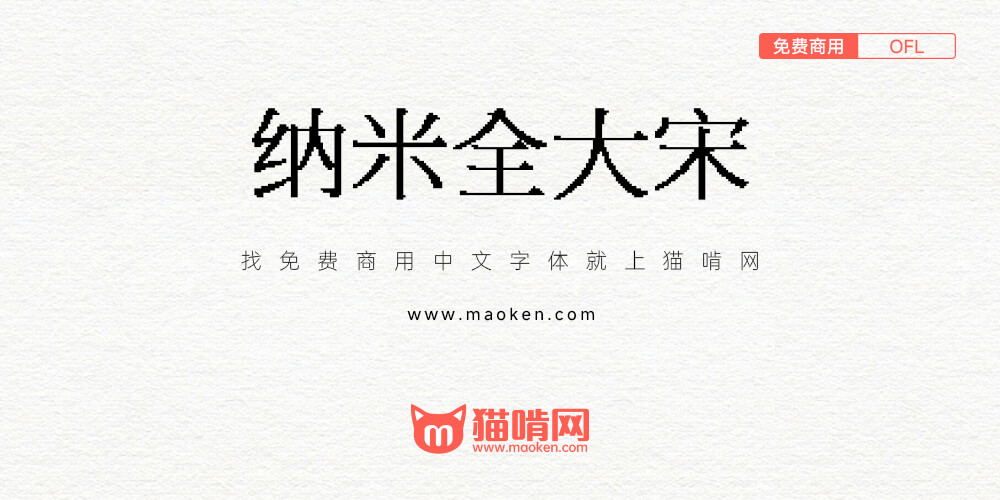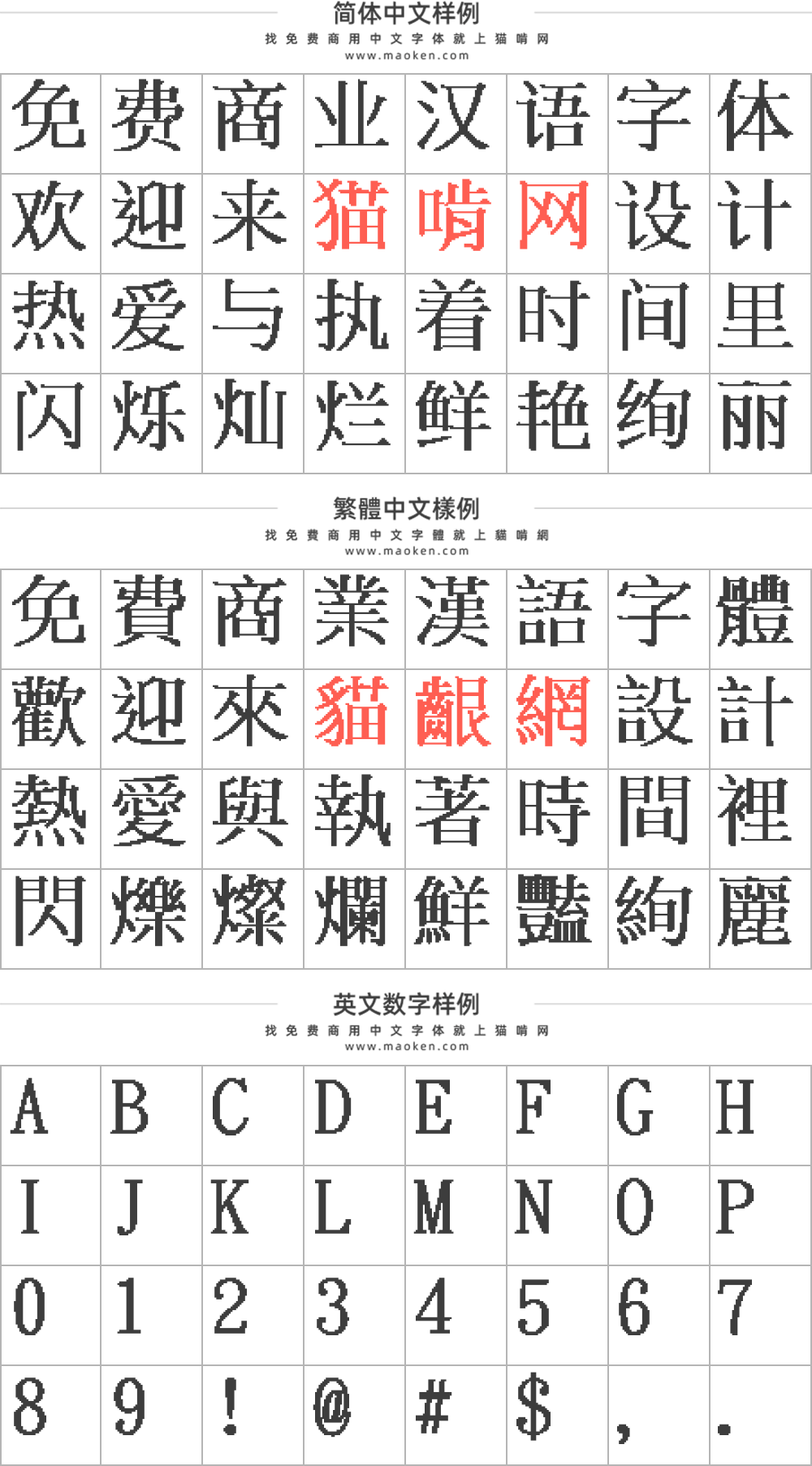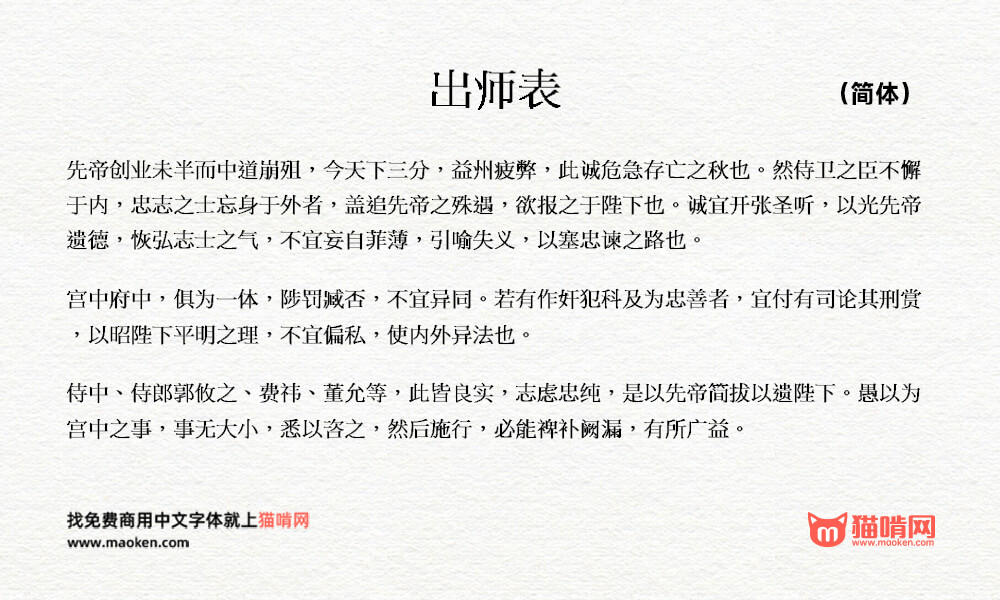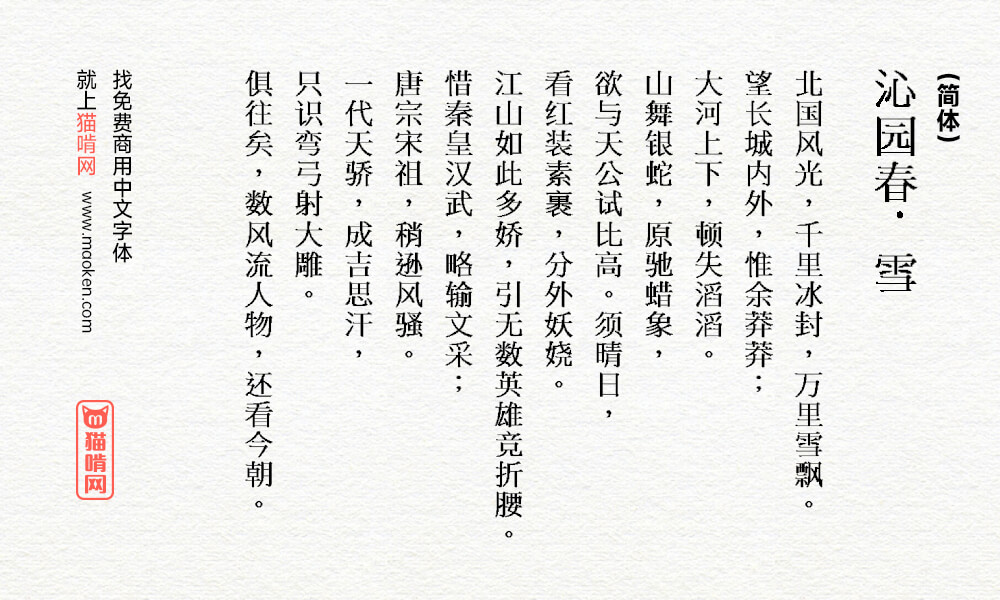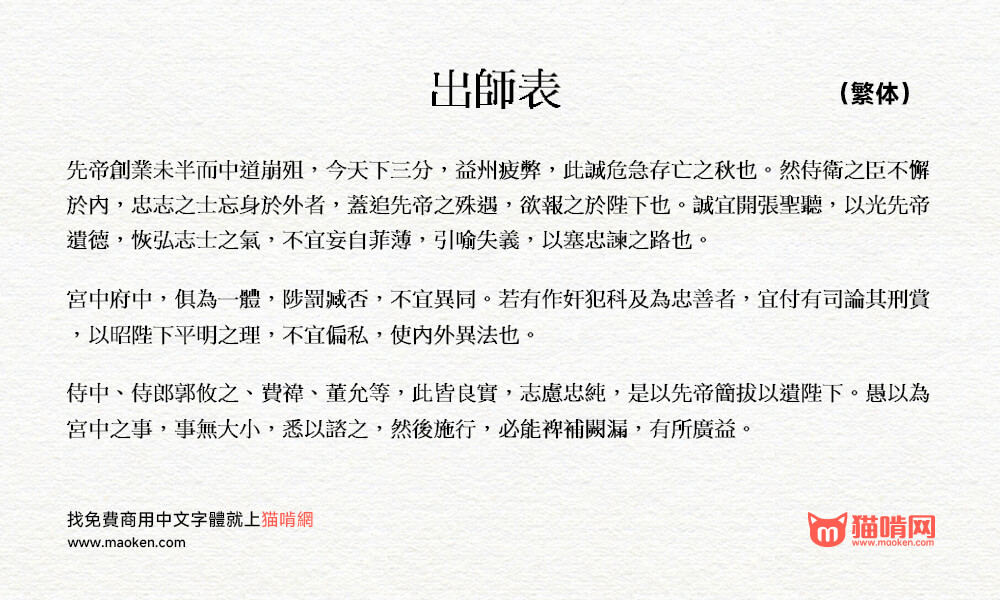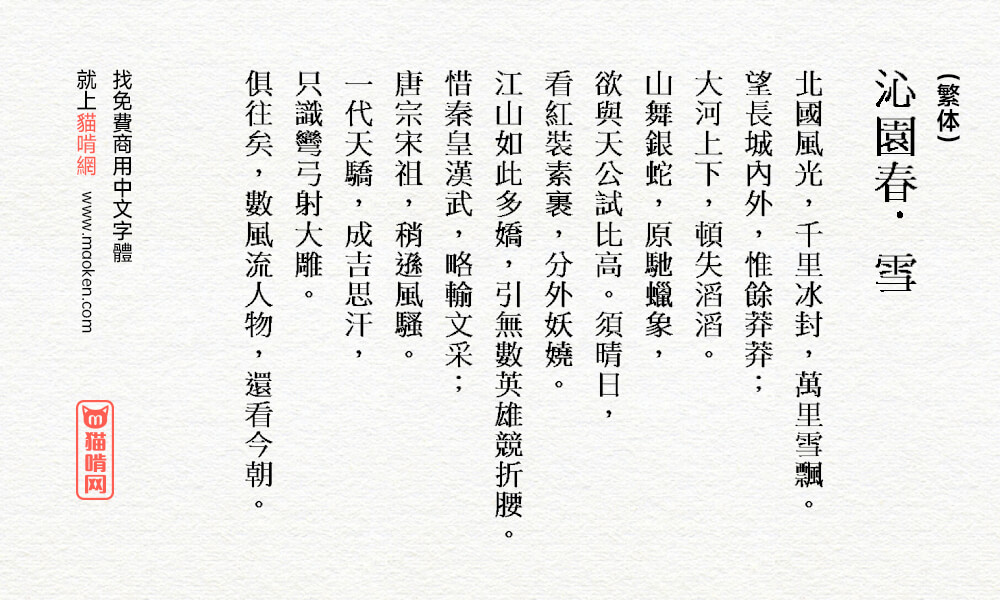
| 字体作者:寒沙 (中国大陆) | 字体字重:1个 |
以全字库正宋體作为基本进行像素制作的像素风格宋体,44×44大小的字符加上泛中日韩的字符支持
收录字形一览
未打勾的为不支持或部分支持的区域,打勾的为已经全部支持的区域。
- 表意文字区域
- ✔基本区
- ✔A区
- ✔B区
- C区
- D区
- E区
- F区
- G区
- H区
- I区
- J区
- 兼容区
- 兼容补充区
- 字符集
- WENZHOU_DIALECT
- ✔GB2312-80
- ✔BIG5
- ✔GBK
- 通规
✔三级字以外
三级字 - GB18030-L2
- GB18030-L3
- ✔CNS11643
- ALL-CHUNOM
Ver 2.1(2025/05/25)
- 新增字符:
𬆄𫢩𫫥𬧐𱜢𱺵𮍄𰻝𰻞 - 新增私用区字符:
F000..F002
Ver 2.0(2025/05/18)
- 将大小从40×40增大至44×44
- 原本是以CNSX_40.bdf做为基本字体,v2.0开始现以全字库正宋体为基本模板进行制作大字库字形(A为第零平面,B为第二平面)
Ver 1.0(2025/04/30)
- 纳米全大宋发布。
英文数字间距也太大了,改一改吧
完全变成新细明体了wwww
这个字体有意思,我记得0几年,液晶显示器刚出现那会,显示文字的效果差不多就这样